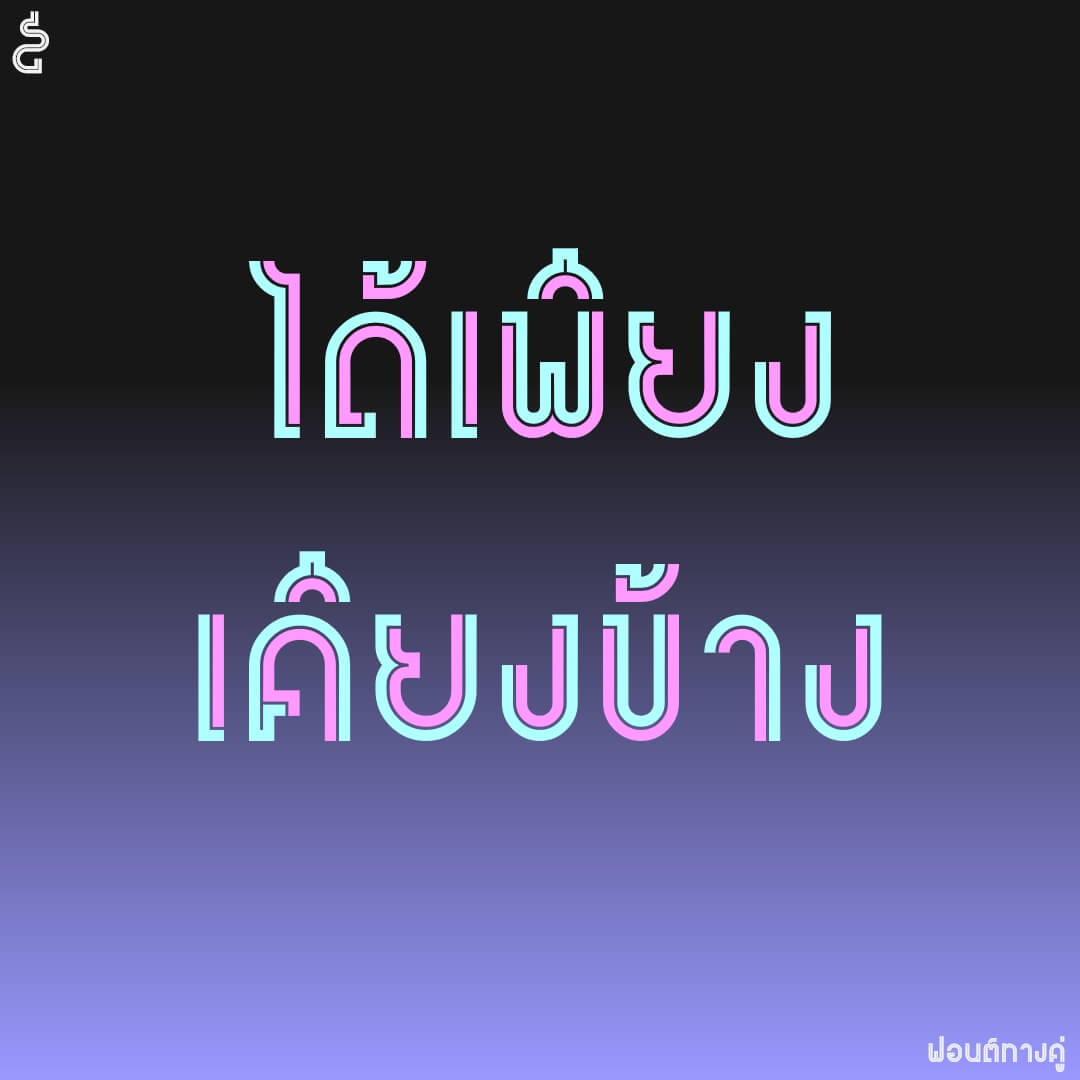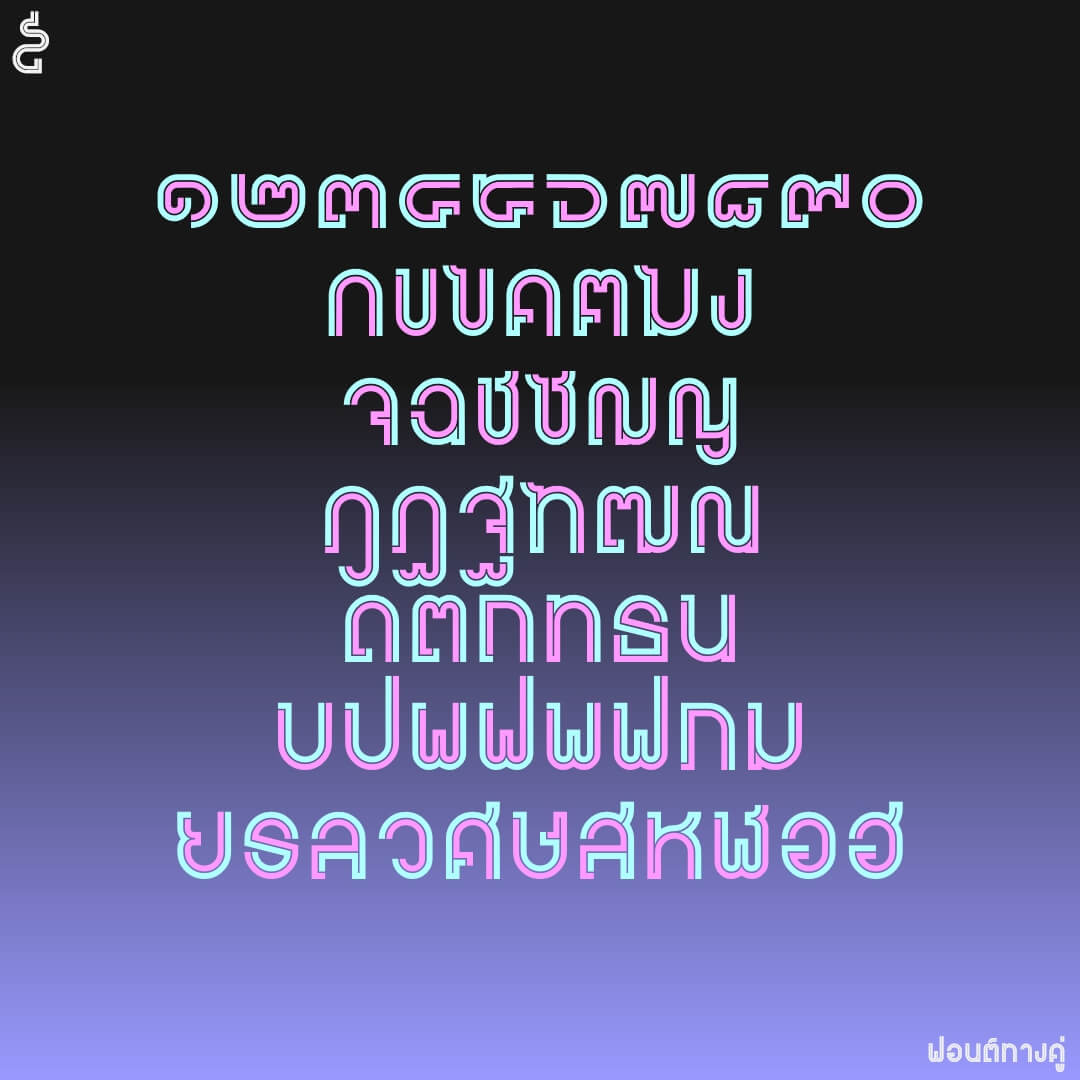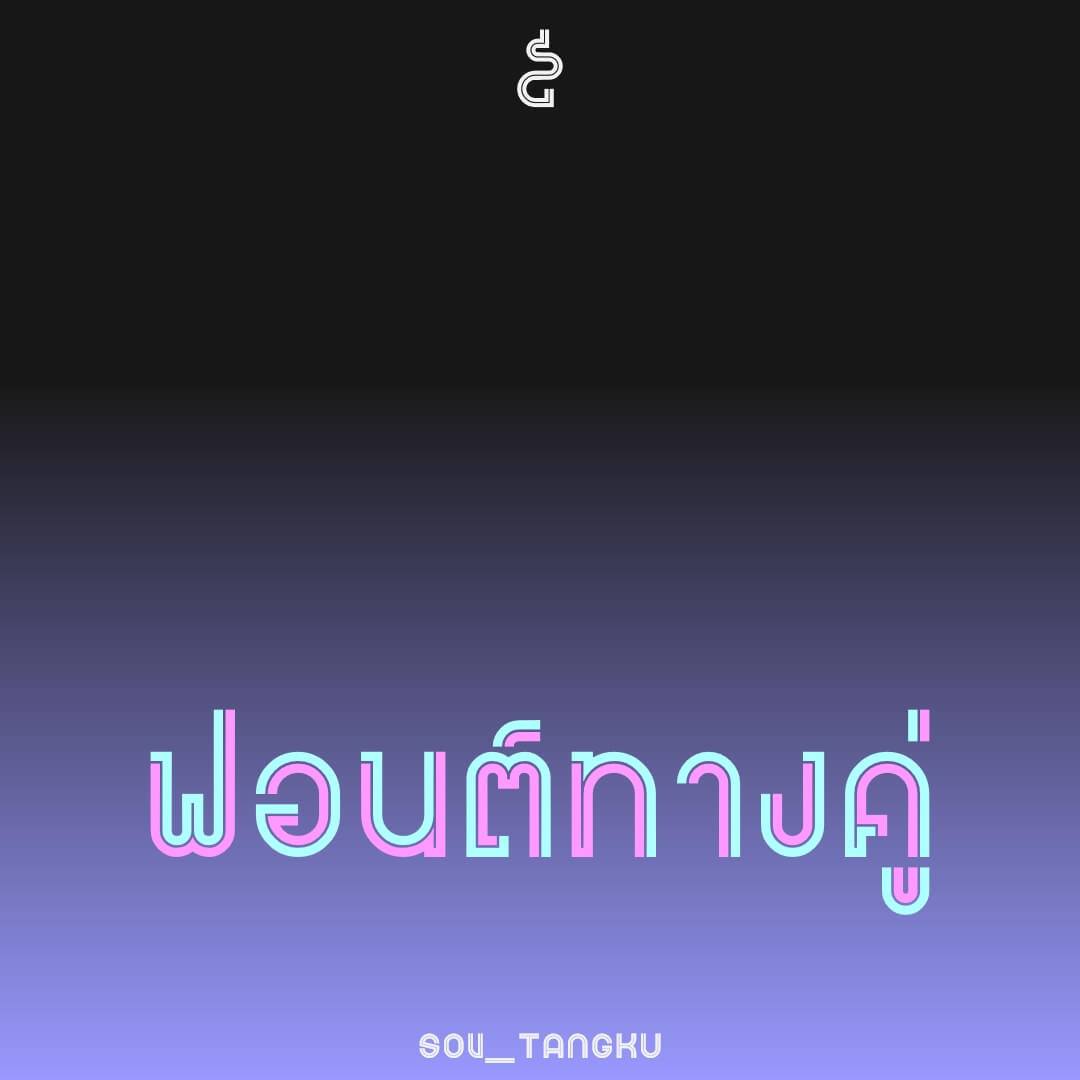
ฟอนต์ทางคู่ – อักษรไทยไม่มีหัวแต่มีหัว ตัวเดียวแต่สองฟอนต์ ทำสองสีได้ เวลาใช้ยุ่งหน่อย ต้องซ้อนตัวปรกติ กับตัว bold
เบื้องหลังการออกแบบ : ฟอนต์ ทางคู่
ทางคู่ (SOV_Tangku)